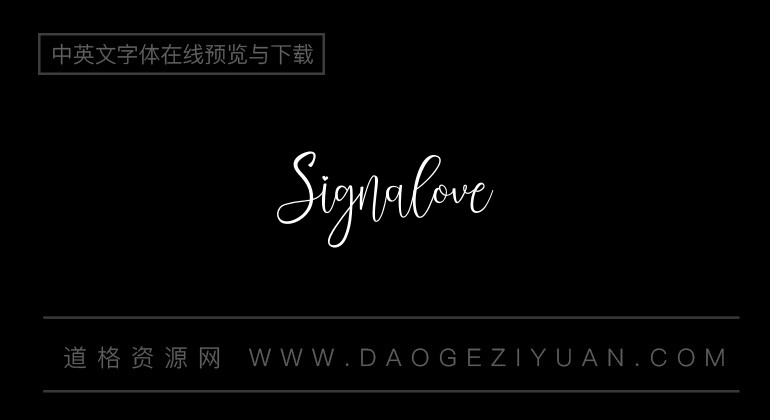
Signalove字体是一款专为设计师量身打造的润色护眼字体,用于视觉设计、排版、印刷和网页设计等。它有一种独特的、柔和的、清新的外观,能够使字体更加清晰而自然,有助于改善视觉效果,从而让文字变得更加易读。它非常适合用于网页设计,能够让网页内容更加精美,更容易被用户接受。此外,它还具有护眼功能,能够有效减少眼睛的疲劳,从而让用户更加舒适。内容介绍
Signalove是一款非常不错的手写艺术字体,具有很好的视觉感,适合于文化类的宣传设计、商业类品牌的广告和产品包装设计以及个性化文字排版等较多场景。